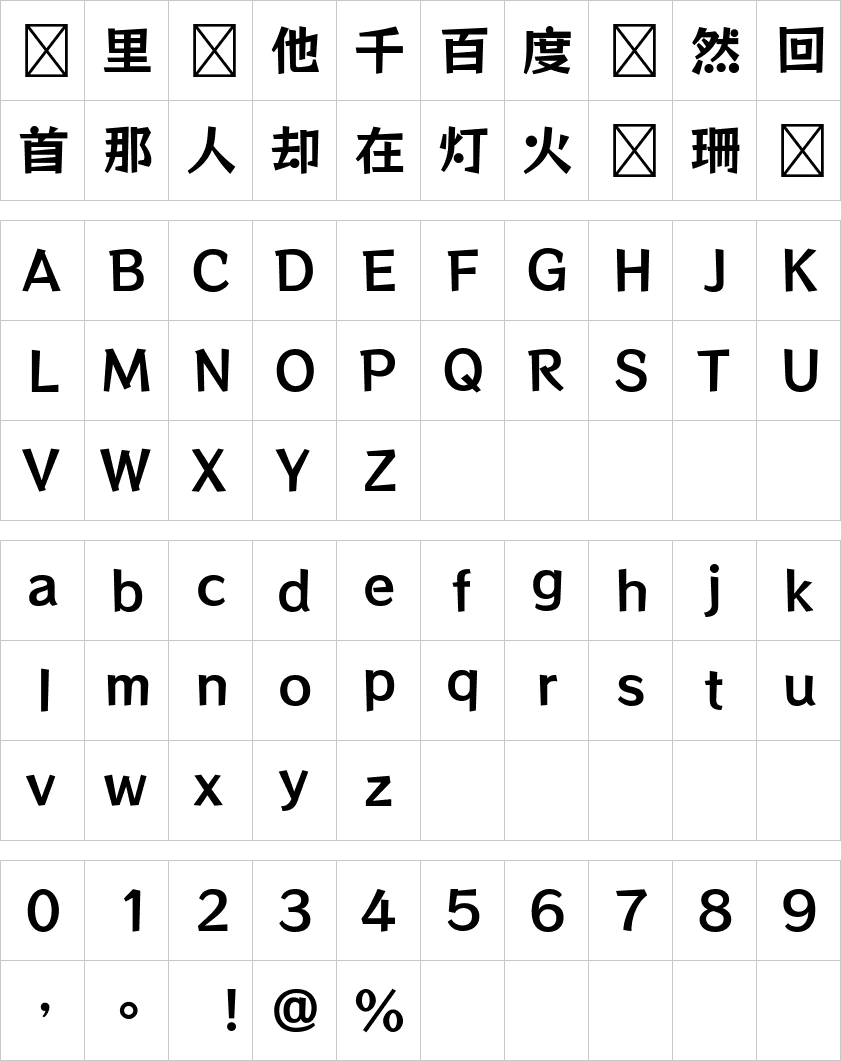
ロックンロール One
摇滚乐 One(日文名:ロックンロール)是日本著名字体设计公司Fontworks免费开源一款字体,是原始的流行风格字体。力度不同的笔触增加了动量,而圆点则营造出生动活泼的感觉。摇滚乐 One这个字体名称是猫啃君为了让大陆的小伙伴方便记忆而根据翻译的而来的中文字体名称,并未对字体作任何修改。